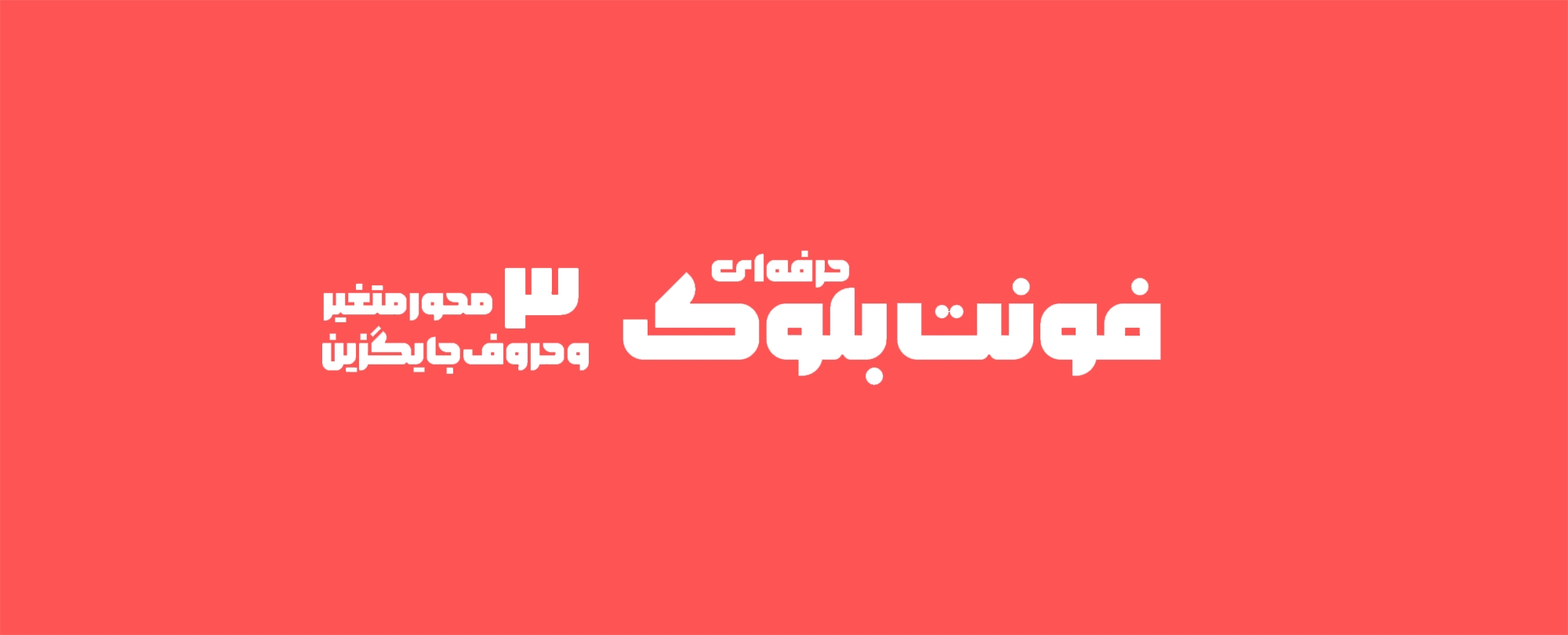
فونت بلوک
فونت بلوک با کنار هم گذاشتن بلوک‌های مربع و مستطیل ساخته شده است.
بلوک فونتی ساده، هندسی و منظم است، و به دلیل وزن سنگین بیشتر برای استفاده در عناوین کوتاه مناسب است.
در دیزاین حروف بلوک از خط کوفی بنایی یا معقلی الهام گرفته شده ، خط بنایی یا معقلی به دلیل ارتباط عمیقش با آجر و ساختمان ساختار مبتنی بر مربع و مستطیل داشته است.
تایپفیس بلوک دارای دو استایل نرم و سخت یا Round و Sharp است که هرکدام از آنها شخصیت متفاوت و مجزایی دارند و بهتر است متناسب با موضوع و محتوا از آنها استفاده نمایید.
فونتی مناسب  تایپوگرافی و استفاده در طراحی پوستر و کاورهای خلاقانه.
استایل‌های فونت بلوک
فونت بلوک بطور کلی در دو استایل فرمی و شخصیتی پیاده سازی شده است: استایل سخت یا Sharp که دقیق، منظم، خشک، جدی و کمی وسواسی است و استایل نرم یا Round که شخصیتی نسبتا مهربان، صمیمی و دوستانه‌تر دارد، درک مناسبتری از احساسات دارد و با مخاطب با قولِ‌ لیّن‌تری صحبت میکند و به قول معروف سعی میکند با گفتگو مسئله را حل کند!
درمورد هردو استایل امکان تغییر فرم حروف و نوع نقطه‌ها، میزان نرمی و قوس گوشه‌ها و همچنین استفاده از ترکیبات جایگزین و کشیدگی‌ها بصورت مجزا فراهم است.
در نسخه‌ دوم فونت بلوک علاوه بر این دو استایل در سبک عادی یک سبک نسبتا فشرده یا Condensed به بسته‌ اضافه شده که در این سبک برخی حروف بجای امتداد در محور افق، با افزایش یک ردیف ارتفاع بیشتر امکان فشرده تر شدن افقی نوشتار را فراهم میکنند و این موضوع در مجموع میتواند دست دیزاینر را در چیدمان هرچه بهتر بازتر کند…
سبک کاندِنسد (فشرده) سبکی رایج در بین تایپفیس‌های لاتین بوده که به تازگی بطور پخته تری وارد فضای نوشتار فارسی نیز شده است…
برای ایجاد تنوع بیشتر از قابلیت‌های خط بنایی بیشتر استفاده کردیم و در نتیجه‌ تعدادی مفردات و ترکیبات جایگزین به حروف اضافه شده  که به کاربر امکان خلاقیت و نوآوری بیشتری را ارائه میدهد.
همچنین برای انعطاف بیشتر و تناسب بین فضاها امکان ایجاد کشیدگی های نوین به حروف فونت بلوک اضافه شده که به کاربر امکان میدهد تا بجای دفورم کردن حروف و یا ایجاد فضای خالی نامتناسب خود حروف را تغییر دهد.
چراغ فونت بلوک از آنجایی در ذهن من روشن شد که خلاء و کمبودی را در فضاهایی حس کردم که عناوین کوتاه می‌بایست برجسته و تاثیرگذار ظاهر شوند اما به دلیل عدم پیشرفت تایپ فارسی در یک بازه‌ی محدود و تمرکز بیشتر دیزاینرها بر تایپ‌فیس‌های متن، به این فضا توجه کمتری شده و تایپ‌فیسی که مناسب این فضا باشد و از فرم نوآورانه‌ای برخوردار باشد کمتر یافت میشد.
تعداد محدودی از تایپ‌فیس‌های موجود هستند که هنوز هم علیرغم تحول تایپ فارسی جزو انتخاب های اول و اصلی طراحان گرافیک و تابلوسازان هستند.
تایپفیس هایی مانند تیتر، یکان، زر، نازنین، میترا و غیره که عمدتا تاثیر زیادی از خط نسخ گرفته اند در زمان خودشان شاهکار بودند اما استفاده‌ی مکرر از آنها و راکد ماندن این فضا برای مدتی طولانی از جذابیت های فرمی این تایپفیس‌ها به شدت کاسته.
به همین علت سعی کردم تا حد قابل توجهی از خط پر استفاده‌ی نسخ فاصله بگیرم و دربین رسم الخطوط فارسی/عربی خط بنایی یا معقلی را برای این فضا مناسب تر دیدم به این علت که این خط برخلاف خیلی از خطوط دیگر که با خوشنویسی بوجود آمده اند با کنارهم قرارگرفتن بلوک‌های آجری پدید آمده و همین موضوع تناسب بیشتری را برای فضاهایی مثل تابلو یا کتاب که ابعادی مستطیل شکل و هندسی دارند فراهم میکند.
البته خط بنایی به خودی خود خطی خشک و بشدت سخت خوان است و معمولا استفاده از این خط در کتیبه‌ها و تابلوها بیشتر متمرکز بر تناسب فضاهای مثبت و منفی بوده تا خوانایی.
اما داشتن کرسی متحرک، انعطاف و تنوع بسیار بالا در حروف، تناسبات به شدت دقیق و هماهنگ، سواد و بیاض به شدت تکامل یافته و نزدیکی فرم برخی از حروف به خطوط دیگر مزیت‌های خط بنایی بودند که مرا جذب کردند.